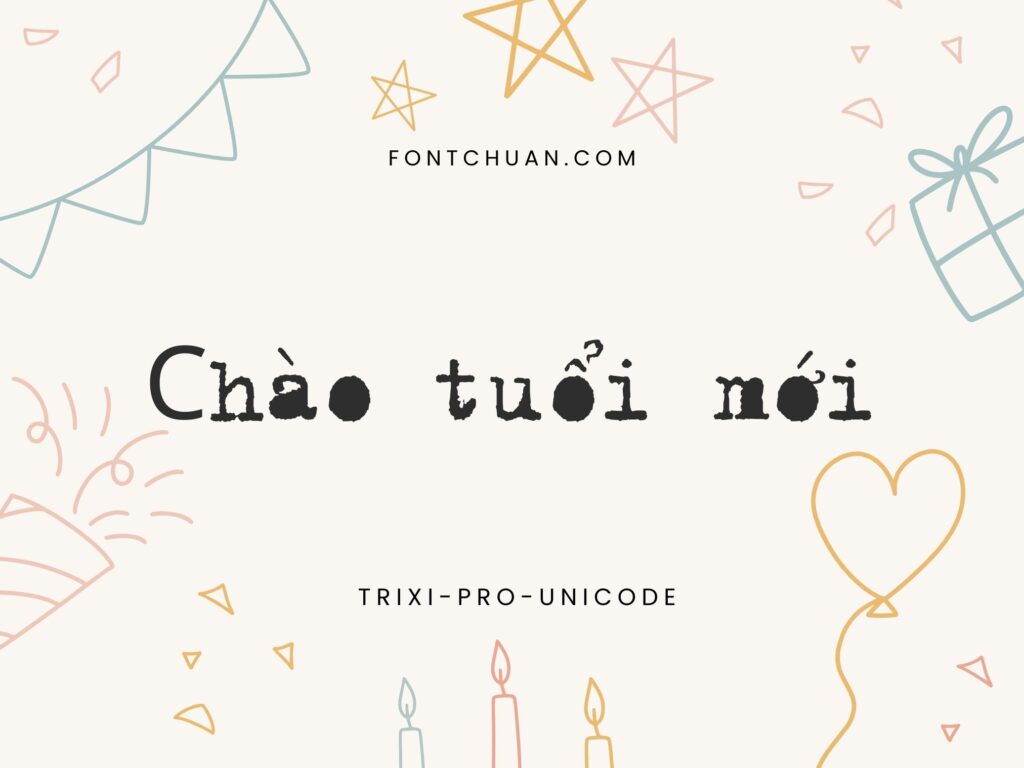
Font Trixie Pro Trọn Bộ Việt Hóa
Tác giả Font: Erik Van Blokland
Việt hóa bởi: Bdesign
Trixi Pro là một font chữ mang phong cách máy đánh chữ cổ điển, được thiết kế bởi Erik van Blokland và phát hành bởi FontFont. Font này có các biến thể như Light, Regular, Heavy và Rough, với các nét chữ mô phỏng hiệu ứng mực in không đồng đều, tạo cảm giác vintage và hoài cổ. Phiên bản Việt hóa được thực hiện bởi cộng đồng, hỗ trợ đầy đủ tiếng Việt và nhiều ngôn ngữ khác. Font được sưu tầm và đăng bởi thành viên của Font Chuẩn.
Với thiết kế chữ đơn giản nhưng gồ ghề, Trixi Pro tạo nên sự chân thực và cổ điển, phù hợp cho các thiết kế như poster, bìa sách, thiệp mời và các ấn phẩm truyền thông cần sự độc đáo và nghệ thuật. Font này cũng có thể được ứng dụng như một Font chữ ẩm thực, giúp các nhà hàng, quán ăn hoặc thương hiệu thực phẩm thể hiện phong cách vintage, độc đáo và thu hút trên menu, bao bì sản phẩm hoặc biển hiệu. Ngoài ra, Trixi Pro còn được tận dụng hiệu quả trong các ngành quảng cáo, giáo dục, thiệp cưới, cũng như các sự kiện như lễ hội, sinh nhật, ngày Nhà giáo và Valentine.